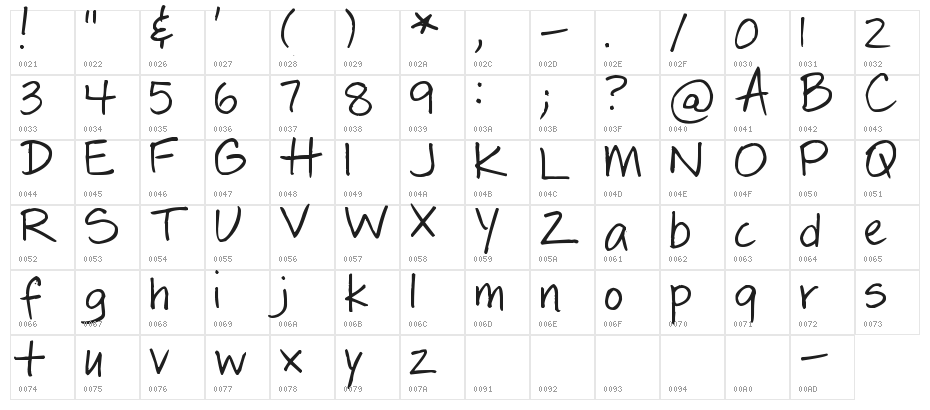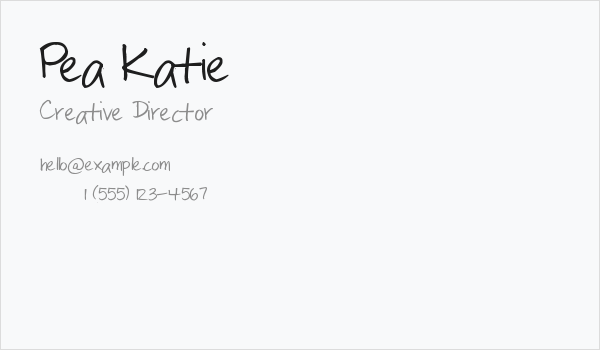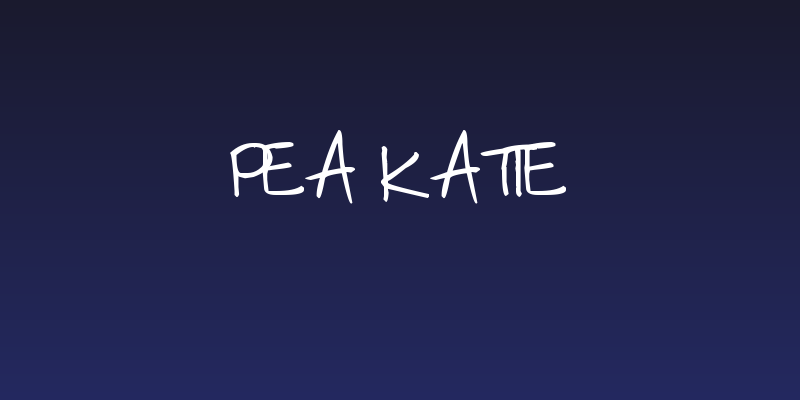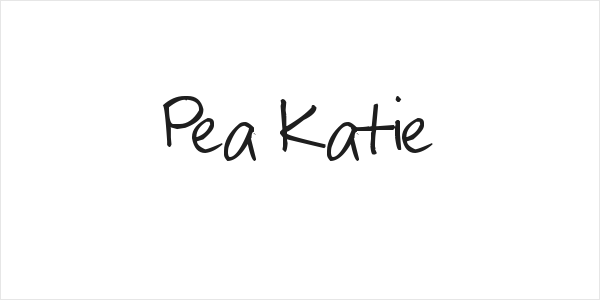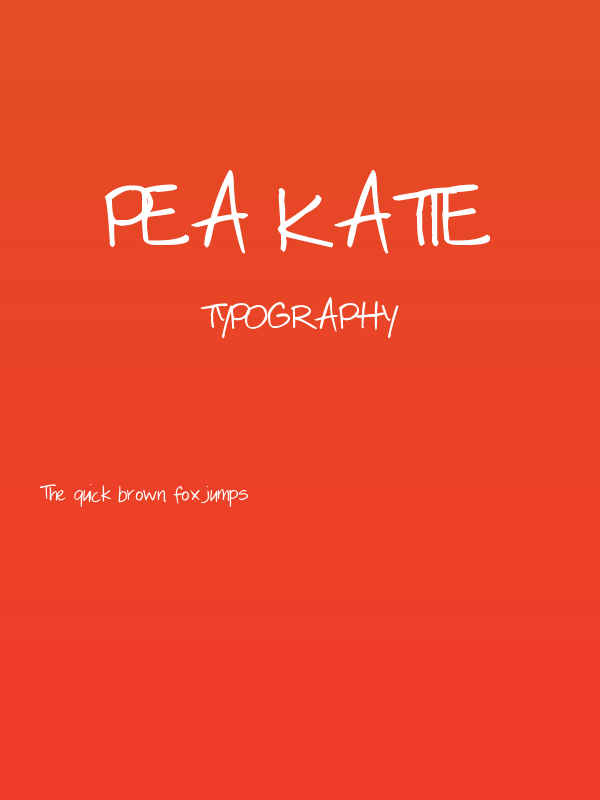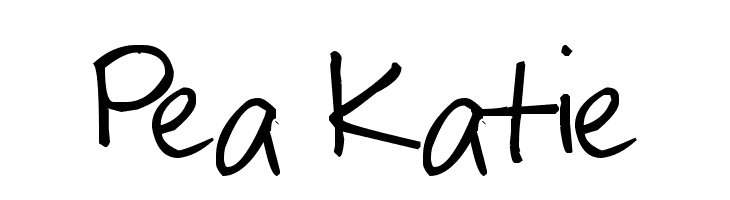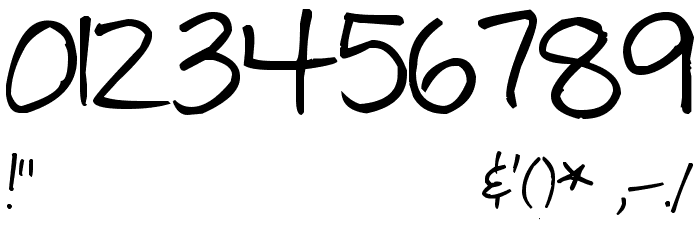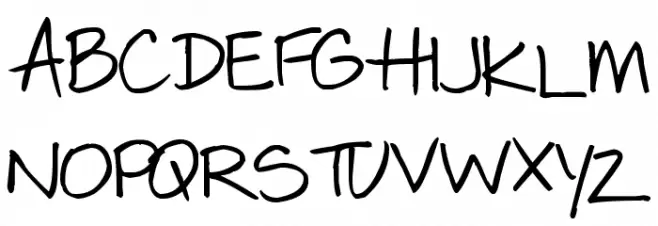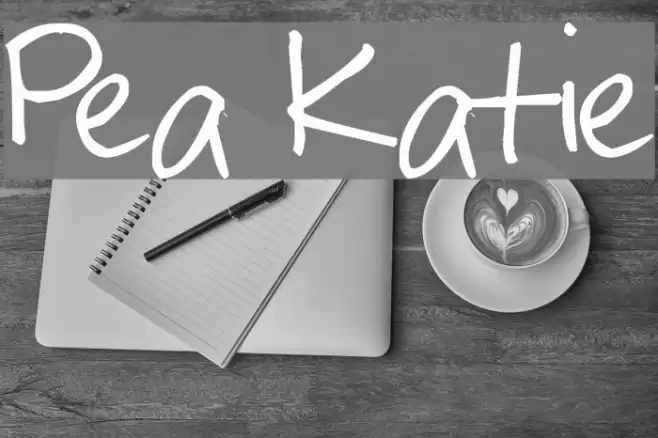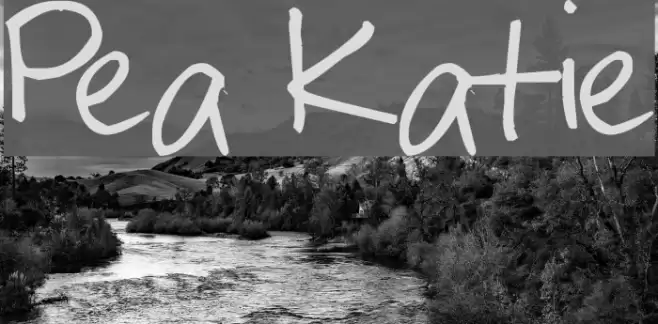
Pea Katie Font
PEA-KATIE 大文字
PEA-KATIE 小文字
PEA-KATIE その他の文字
| 全体的なスタイル | Casual, Playful |
| 用途 | Greeting cards, Social media graphics, Informal branding |
| おすすめプロジェクト | Ideal for personal notes, greeting cards, social media graphics, and informal branding projects. |